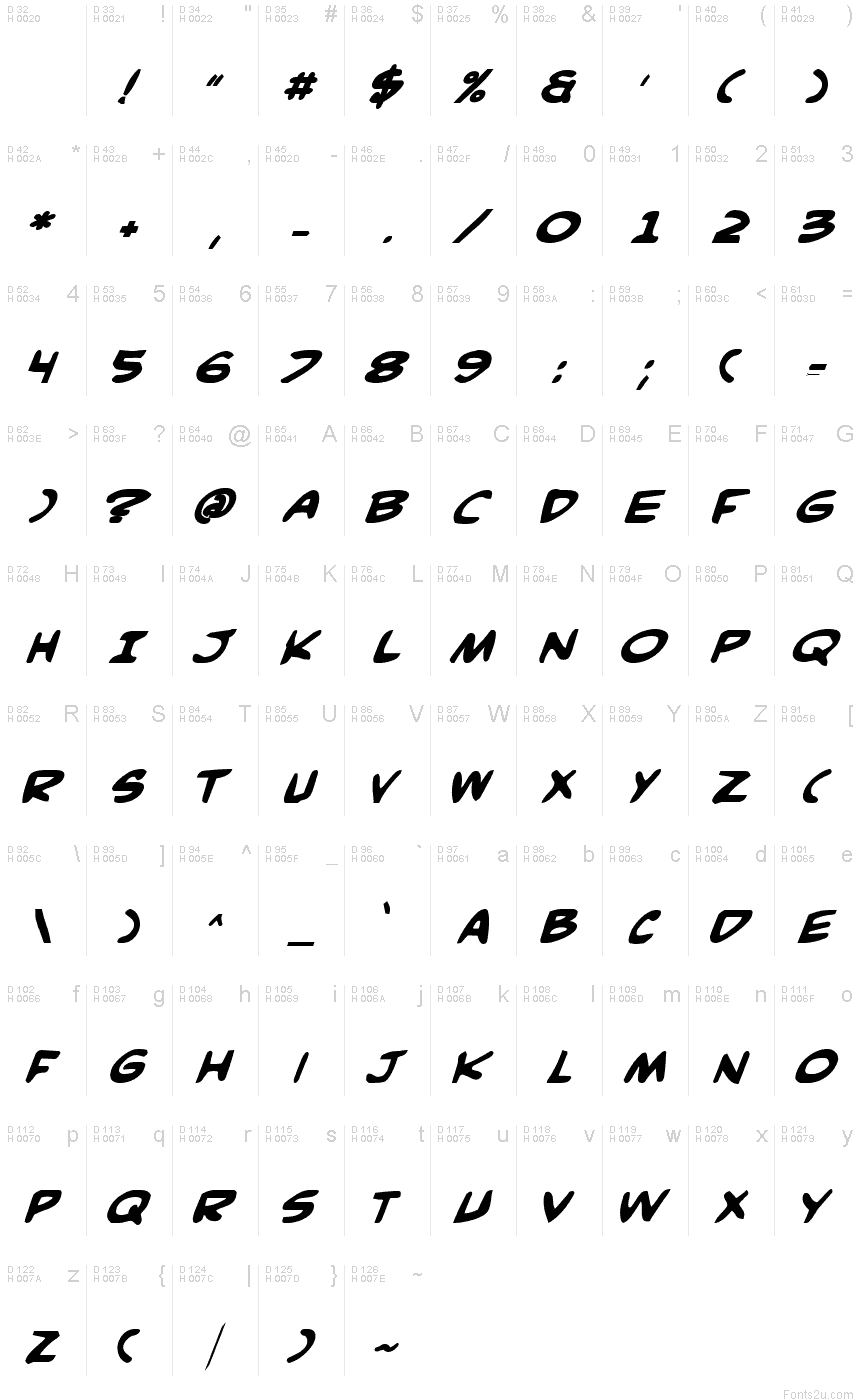
Comic Book Commando Bold Italic
Comic Book Commando Bold Italic od Iconian Fonts to darmowy krój pisma typu display w komiksowym stylu, który uderza w stronę niczym efekt dźwiękowy. Grube, atramentowe kreski i mocne pochylenie nadają każdemu słowu dynamiki, jakby litery rzucały się do walki. Zaokrąglone kształty pozostają przy tym przyjazne i czytelne, a kompaktowe światło między znakami sprawia, że nagłówki są zwarte i wyraziste – to idealne rozwiązanie, gdy potrzebujesz natychmiastowego efektu przy użyciu kilku słów.
Ten darmowy font świetnie sprawdza się na okładkach komiksów, w dymkach, na dynamicznych stronach, plakatach dla dzieci, logotypach gier i miniaturach na YouTube, które wymagają śmiałego, ręcznie rysowanego charakteru. Użycie Comic Book Commando Bold Italic w wersalikach dodatkowo wzmacnia jego energię. W przypadku podpisów lub tekstu interfejsu zestaw go z prostym, neutralnym krojem bezszeryfowym, aby to główne hasła pozostawały w centrum uwagi.